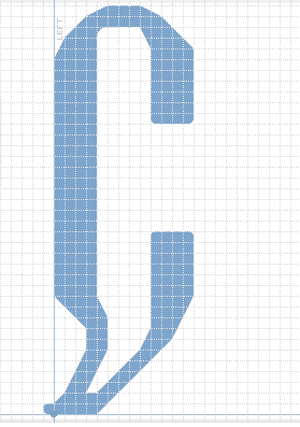
Прикольный шрифт.
Только, имхо, с кривыми больших радиусов беда - но это проблема местных модулей. :)
Поэтому всё хорошо, только O, C, Q и т.п. - слегка смущают. Я бы их скорее так сделал:
я его нарисовала что бы корректировать потом, действительно совсем не то что должно было быть в итоге, но ни как по другому эти кривые не вытянешь. Они должны быть более изогнуты и плавные, нежели сейчас. Спасибо за коментарии:))